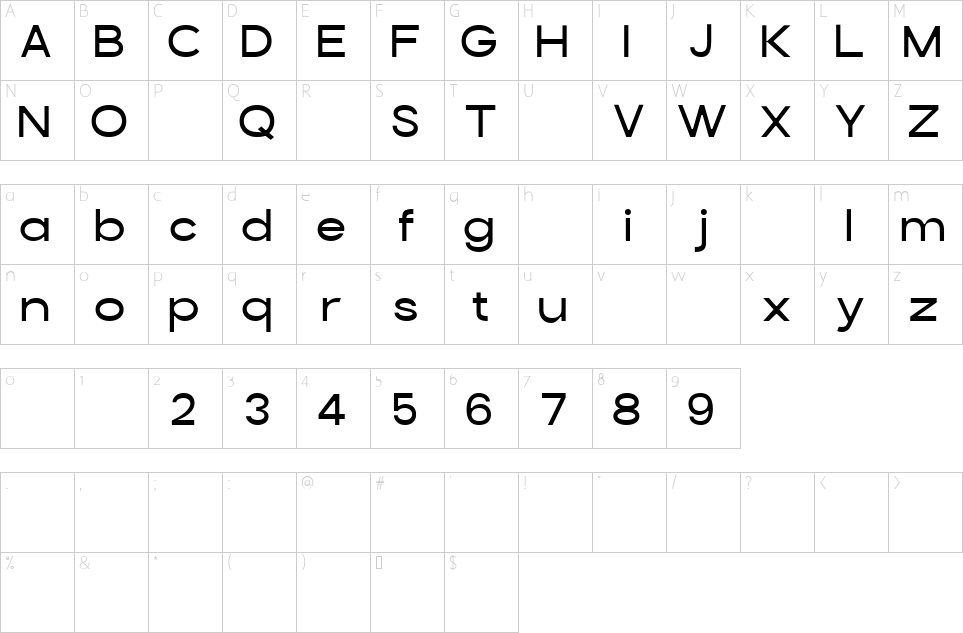
Macaria é uma fonte elegante e moderna, perfeita para criações em diversos estilos de design gráfico. Inspirada no trabalho dos designers independentes, a fonte Macaria foi projetada pela Imoodev. Esta fonte é uma excelente opção para aqueles que buscam uma opção sem custos para incorporar em seus projetos digitais. A cada dia, mais designers descobrem a simplicidade e a versatilidade de Macaria, que lhes permite expressar suas ideias de maneira única e atraente. Com seu design minimalista e moderno, a fonte Macaria é uma ótima escolha para criações que exigem um toque de sofisticação sem perder a personalidade do criador.